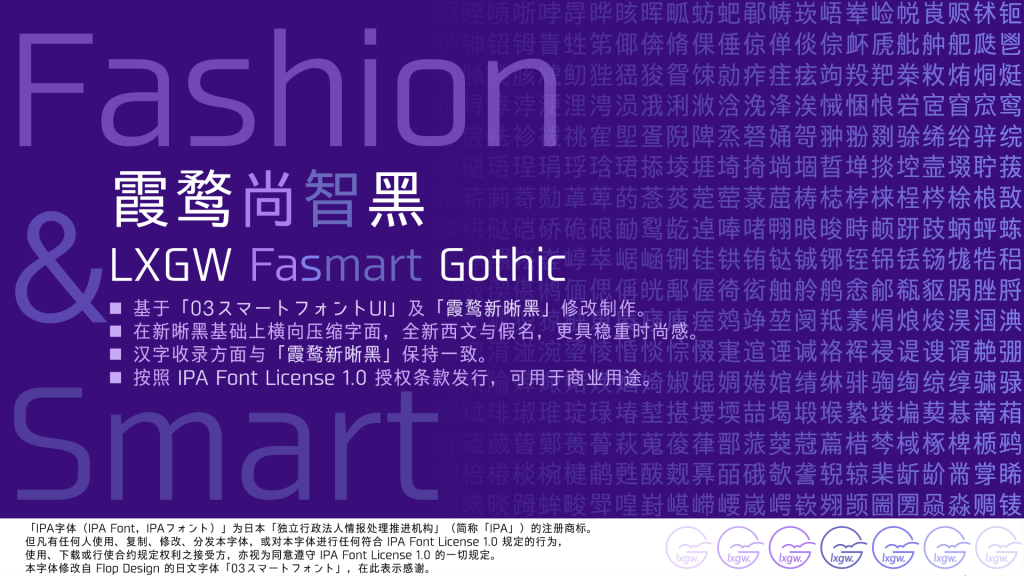
霞鹜尚智黑1.105字体信息
霞鹜尚智黑,在「03スマートフォントUI」的基础上修改制作,将新晰黑字面横向压缩 94%,全新英数与假名,更具稳重时尚感。(注:尚智黑的符号相比于新晰黑会有所欠缺,且可能在后续更新中随时撤消,敬请留意。)
“霞鹜尚智黑1.105”是一款书写很新颖的字体,字体大方,适合各种设计作品使用!欢迎下载!